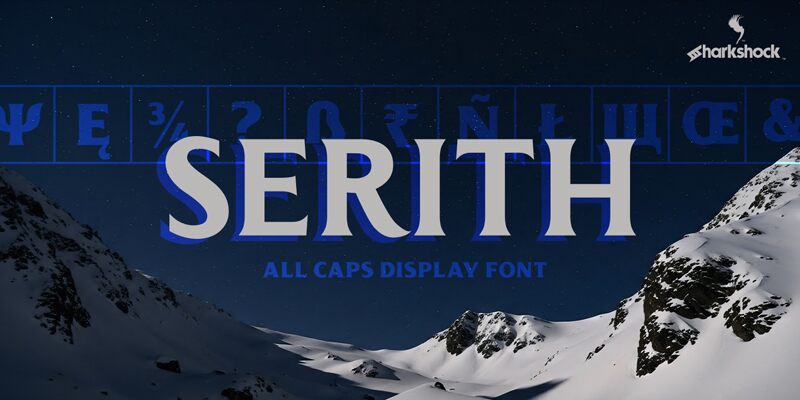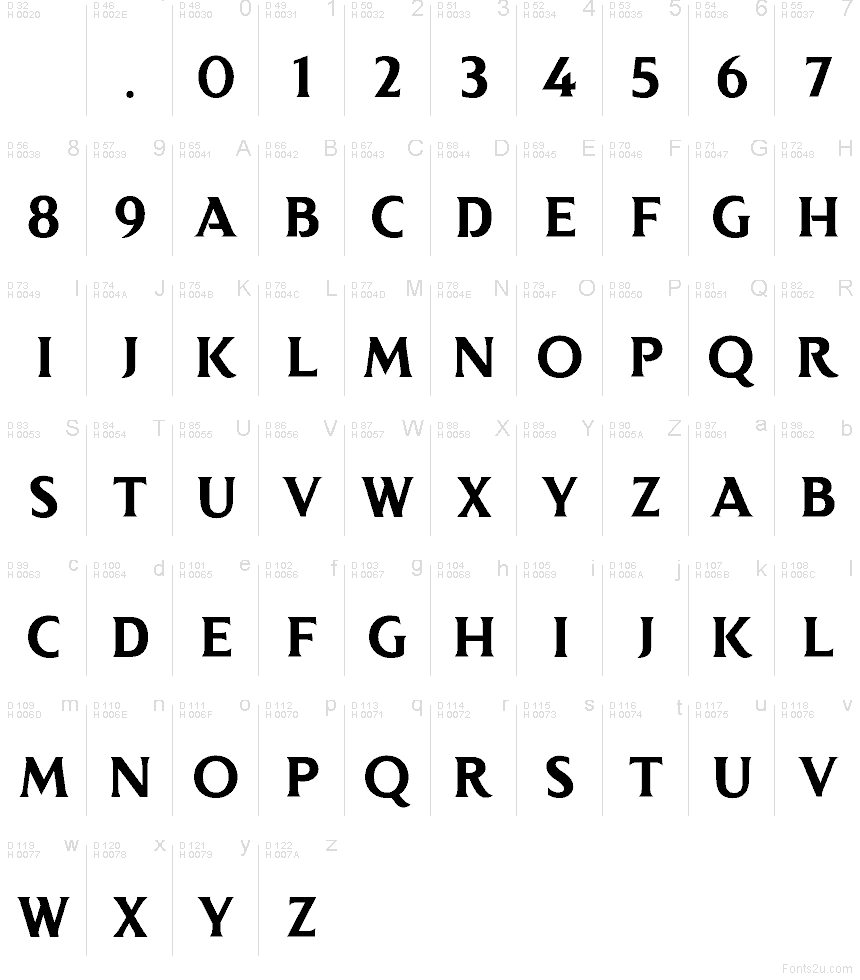
Serith
Serith od Sharkshock je bezplatné patkové písmo inšpirované ostrými rímskymi kapitálkami a výraznou, akoby vytesanou siluetou. Široké vertikálne ťahy, hlboké spoje a špicaté patky dodávajú písmenám charakter vytesaného nápisu, čím sa odlišujú od jemnejšieho dojmu bežných knižných fontov.
To robí zo Serith prirodzenú voľbu pre plagáty, titulky, obaly, knižné obálky a branding, ktorý potrebuje formálny historický nádych. Rytmus vytesaného kameňa dodáva krátkym slovám skutočnú autoritu, najmä v logách, grafike eventov alebo na etiketách, kde má byť typografia v kapitálkach ceremoniálna, a nie všedná.
Serith je písmo typu all-caps. Kapitálky ako B, D a H majú oblúky alebo priečne čiary, ktoré sú čiastočne alebo úplne zošikmené.
- Základná a rozšírená latina
- Diakritika
- Cyrilika
- Gréčtina
- Interpunkcia
- Kerning